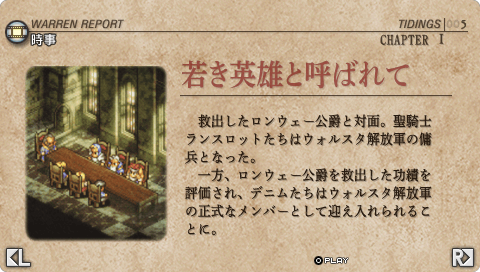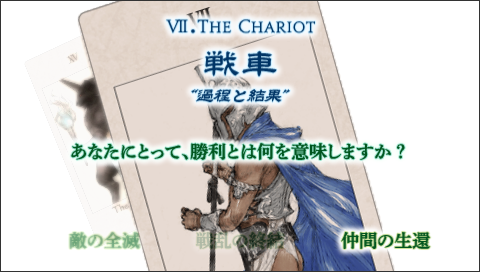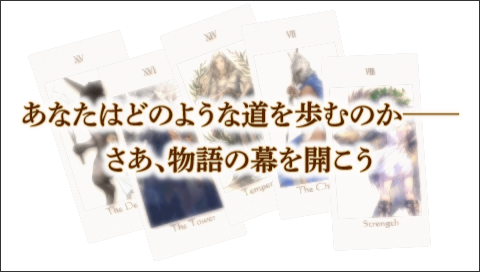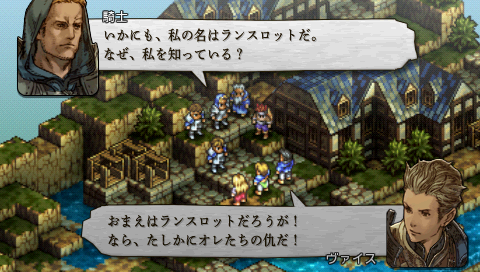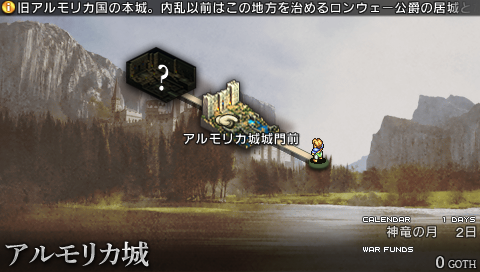
スクウェア・エニックス「タクティクスオウガ 運命の輪」に秀英横太明朝が採用されました
あの名作ゲーム「タクティクスオウガ」が、15年を経て、当時のオリジナルスタッフの手によって、新たに生まれかわりました!
タイトルを耳にして、おっ!と反応してしまう方も多いのではないでしょうか。
1995年に発売されたシミュレーションRPG「タクティクスオウガ」は、長年にわたり多くのゲームファンに愛されている作品です。ゲーム上級者をもうならせた高度な戦闘システム、当時のゲームでは考えられないような美しいグラフィック、そして細かいところまで楽しめるストーリー。
何度も何度もプレイした!というファンも多い「タクティクスオウガ」、ついにオリジナルスタッフが集まり、作品を再構築。いまの時代に向けた「タクティクスオウガ 運命の輪」として完成しました。
そして本作の表示用フォントとして、秀英横太明朝を採用いただきました。
出版物はどんと来いの秀英体ですが、ゲームでの採用は初めて。開発一同、秀英体が無事に仕事を果たせるのか、不安と期待がないまぜでした。しかし実際の画面を拝見して、大喜び! 秀英体の仮名のクラシックな表情が、重厚な世界観にマッチしています。
また、どうしても画面表示の分野では、ゴシック系の後塵を拝することの多い明朝体ですが、小さい画面や細かいグラフィックと一緒でも、その表現力を再確認できました。
秋の夜長に、ゆっくりと「タクティクスオウガ 運命の輪」と秀英体をお楽しみ下さい!